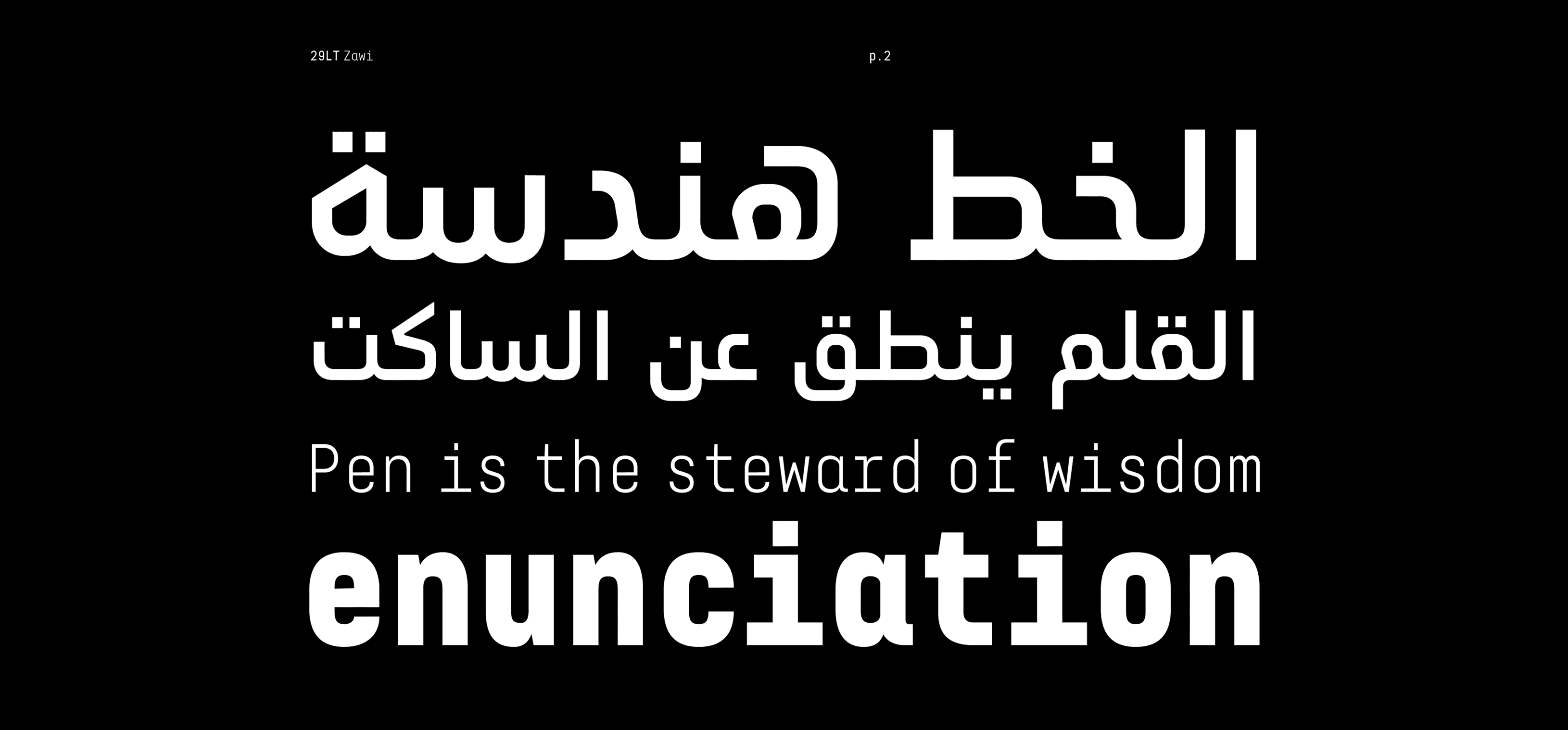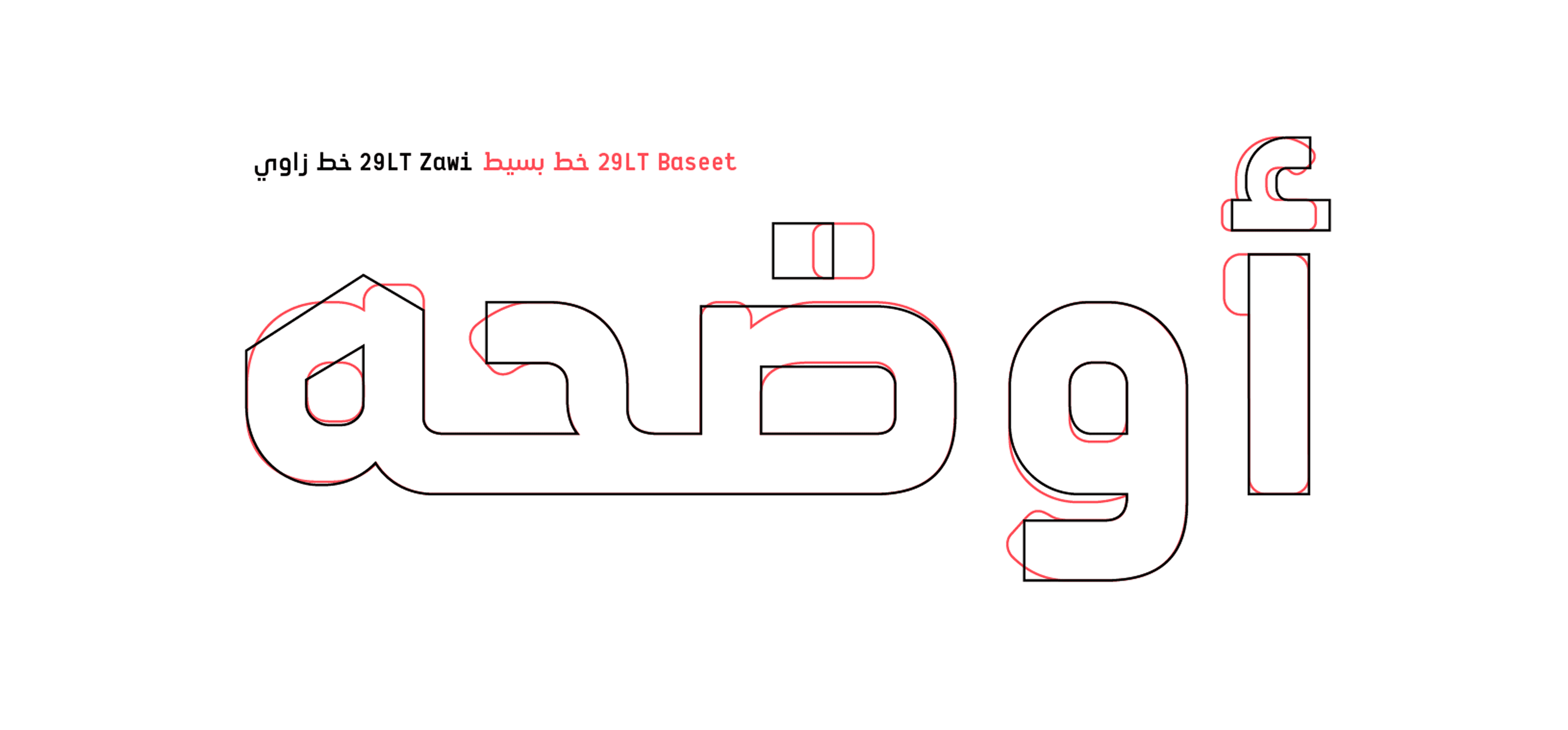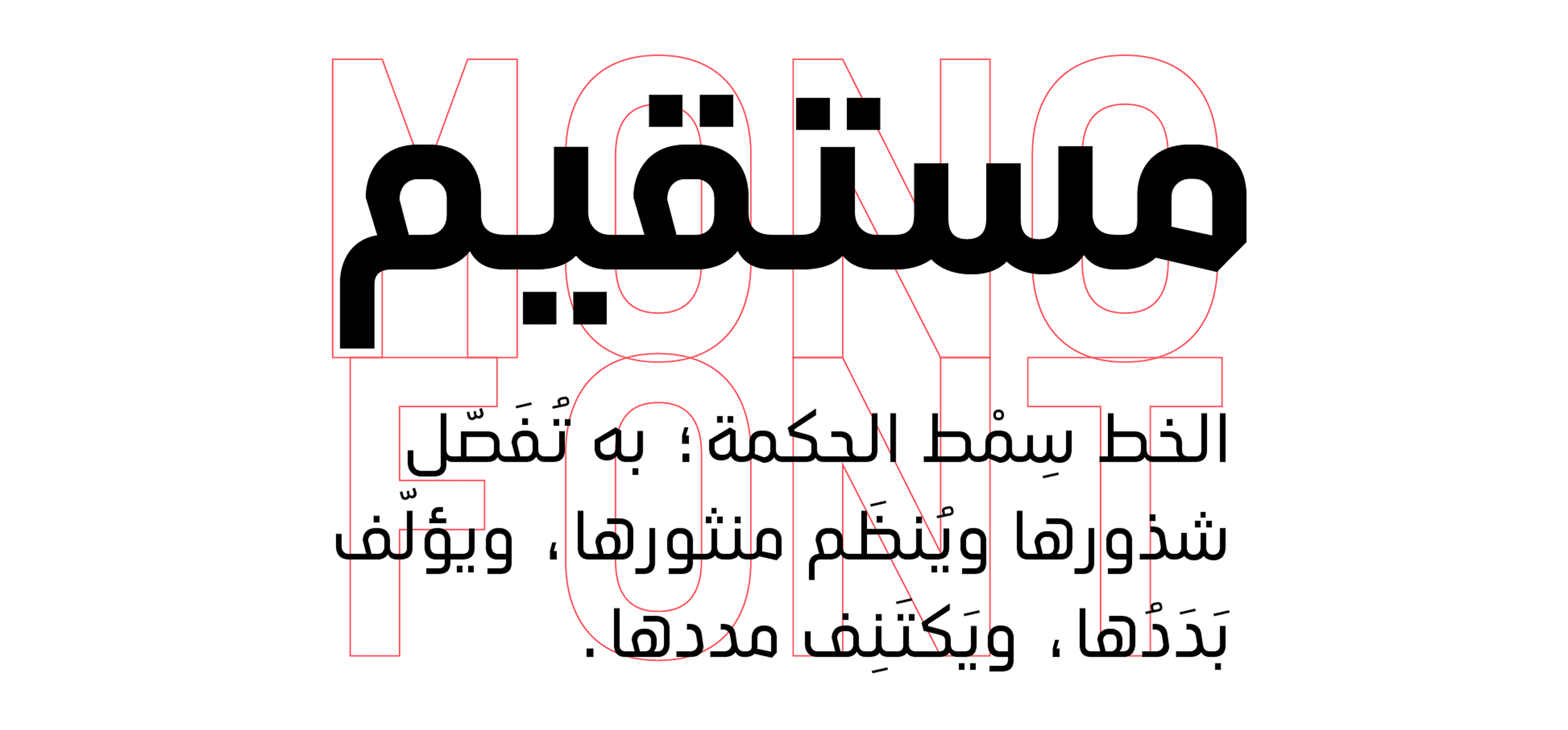
يمتاز خط زاوي بطابع هندسي حاد مستوحى من البنية الخطية للكتابة العربية الحديثة. تم تطويره ليكون خطًا عمليًا وواضحًا يدعم الاستخدامات التحريرية والإعلامية، حيث يجمع بين القوة البصرية والانضباط التصميمي.